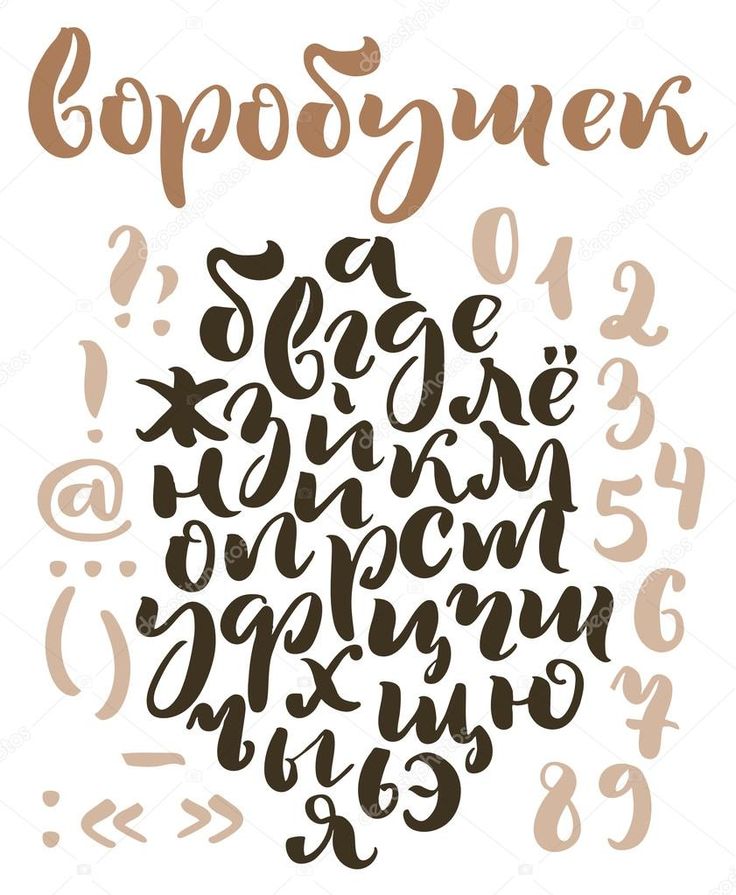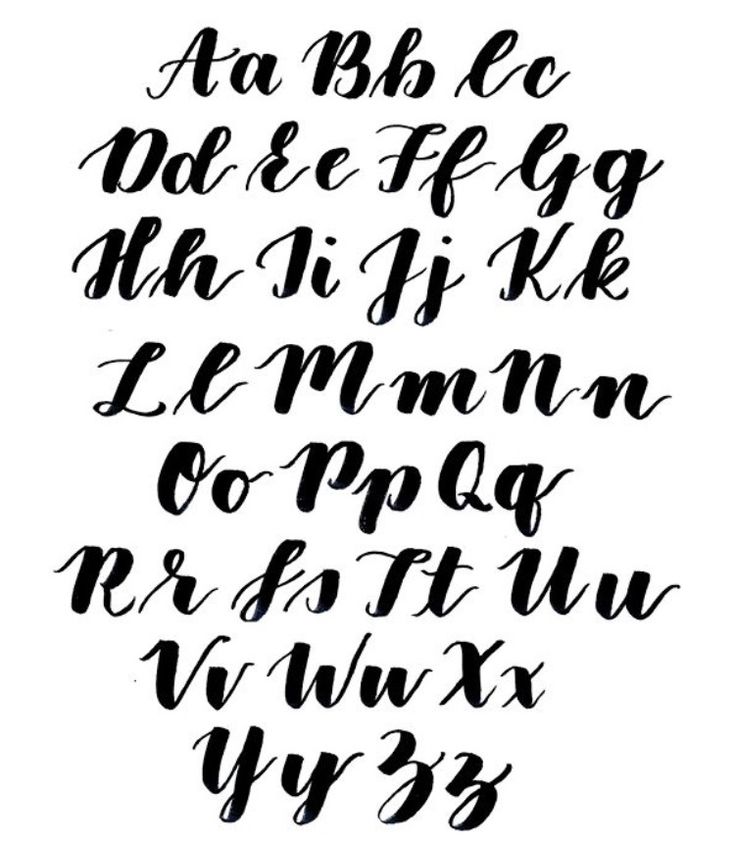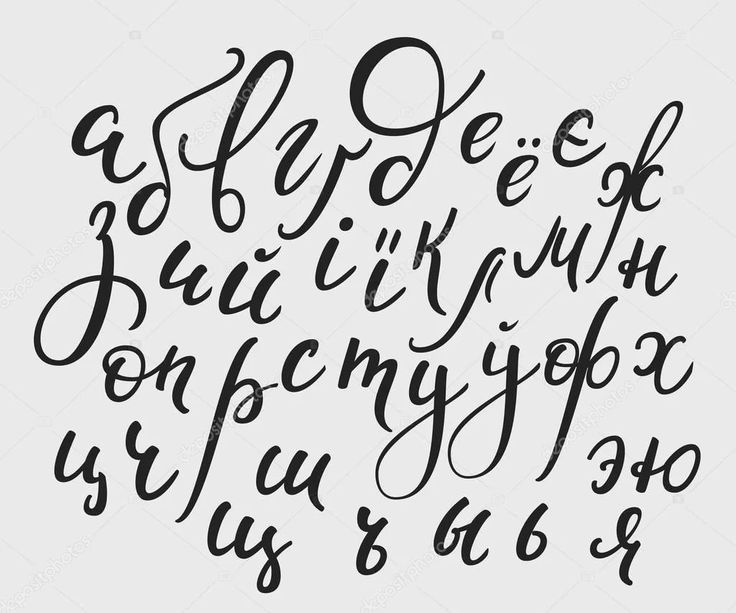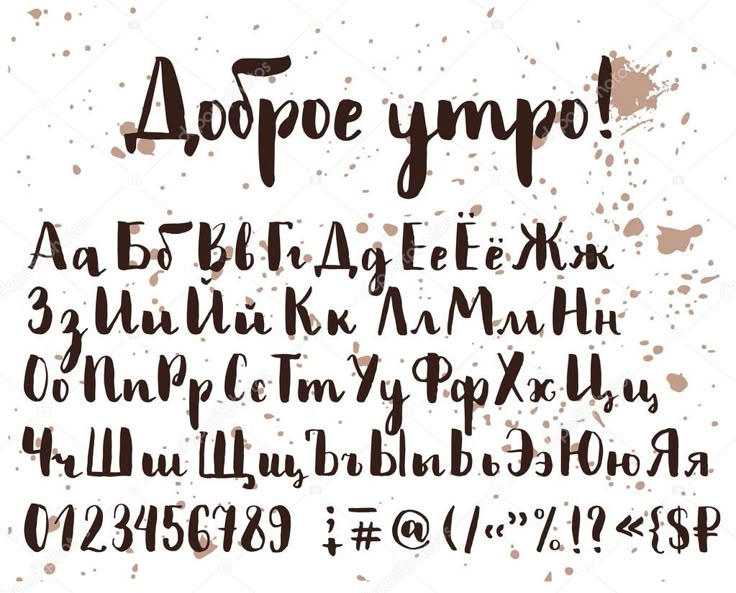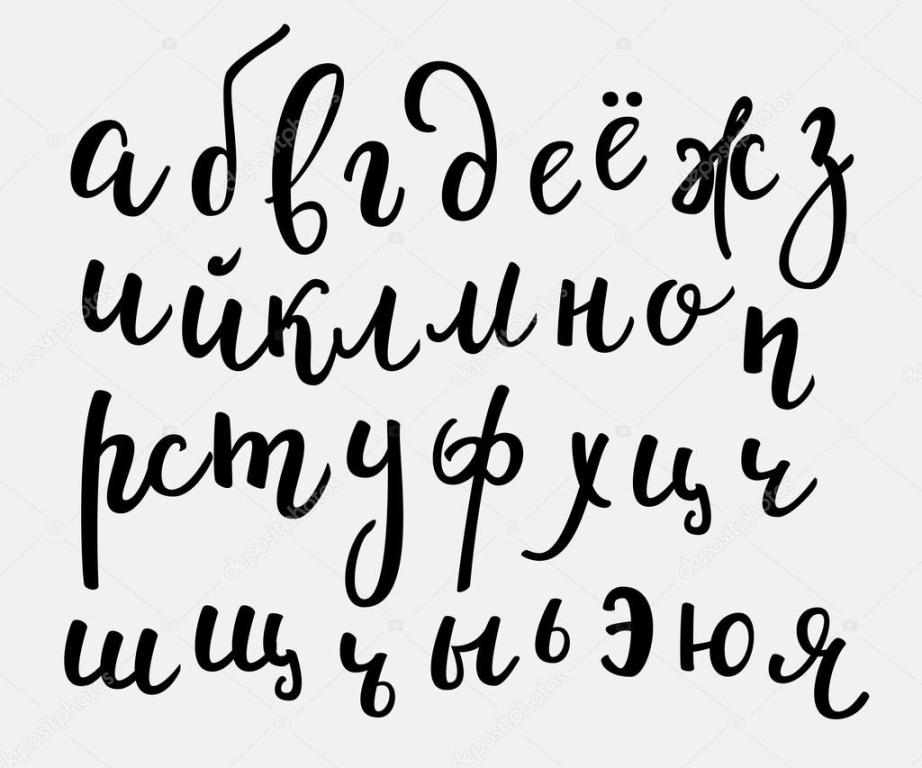
что это такое, чем отличается от каллиграфии
Современный человек окружен рекламой буквально со всех сторон: это и афиши, и баннеры, реклама по телевизору и радио и еще множество других нативных способов, которыми пользуются опытные маркетологи. Одна из последних модных тенденций, которая очень полюбилась дизайнерам, называется леттеринг. Что это такое и почему оно с каждым днем набирает все большую популярность? Давайте разбираться.
Интересное из истории
Каждый знаком с понятием каллиграфии, ведь оно возникло очень давно и сопровождает человека на протяжении всей истории. Сейчас каллиграфия считается атрибутом или даже целым отдельным видом искусства. Однако в далеком прошлом искусство красиво писать имело под собой и практическую почву. Монахи переписывали огромные рукописи и создавали настоящие шедевры, используя самые сложные техники каллиграфии.
Возникла каллиграфия в Древней Греции, в переводе это слово обозначает «красивый почерк». Греко-римское письмо имело свои особенности и отличительные черты от восточно-азиатского алфавита.
При написании текстов даже использовались разные инструменты, так, к примеру, греки писали пером, а китайцы пользовались тушью и кисточками.
В отличие от каллиграфии леттеринг (что это такое, мы разберем чуть ниже) возник в прошлом столетии как яркий и эффективный инструмент рекламы любого товара. Однако сейчас он успел стать течением современного исскуства, к которому обращаются все большее количество дизайнеров, шрифтовых и арт-художников.
Отличия леттеринга от каллиграфии
Многие ошибочно предполагают, что эти два понятия являются одинаковыми по значению. Однако леттеринг, прописи которого рисуются дизайнерами, и каллиграфия — это два абсолютно разных способа написания букв. Если в каллиграфии существуют определенные правила и ограничения, то во втором случае нет никаких границ, художник вправе создавать любые шедевры и воплощать свои самые смелые идеи.
Само слово «леттеринг» с английского языка означает «писать письмо». Основная черта этого направления заключается в том, что это целый рисунок, который состоит из букв и других графических знаков.
Особенности леттеринга
Алфавит, написанный в этом стиле, не имеет своих аналогов, поэтому ни в коем случае нельзя считать леттеринг шрифтом. Ведь шрифт — это готовый набор букв, написанных определенным образом, которые повторно используются много раз. В леттеринге же каждая буква имеет свой неповторимый наклон, толщину и динамику.
Пожалуй, еще одним различием каллиграфии и леттеринга (шрифты считаем отдельным инструментом) является то, что в каллиграфии присутствуют только прописные буквы, запрещены какие-либо добавочные линии и любые мелкие рисунки. А в последнем каждая буква оформляется уникальным образом, дополняется самыми разными картинками и знаками.
Кто этим занимается?
Итак, мы разобрали основы леттеринга: что это такое и в чем его различия от привычной нам каллиграфии. Однако остается еще много вопросов, например, люди какой профессии занимаются леттерингом?
Теоретически, этим может заниматься абсолютно любой желающий, и неважно для каких целей.
Существует множество специальностей, связанных с леттерингом. Вот самые известные:
- типограф, который разрабатывает не только шрифты, но и стили оформления в целом;
- маркетолог-дизайнер, создающий настоящие шедевры рекламы;
- художник, который творит ради искусства;
- тату-мастера, являющиеся самыми молодыми специалистами в этой нише.
Всех этих людей объединяет любовь к волшебному леттерингу, алфавиту (русский или же иностранный — это совсем не важно, ведь текст, написанный с любовью, будет красив на любом языке).
Инструменты для творчества
Древние каллиграфисты писали пером и чернилами. Интересно, а современные художники смогли бы творить шедевры, используя лишь этот примитив? Давайте посмотрим, какими же приспособлениями порадовал специалистов XXI век высоких технологий.
Существует огромное количество самых разных «приблуд» для творческих натур, решивших заняться леттерингом. Для начинающих и для профессионалов имеются свои инструменты.
Итак, вот самые популярные канцелярские принадлежности, которые точно нам пригодятся:
- Брашпены — это инструменты, снабженные картриджем. Напоминают обычную кисть, только их не нужно никуда макать. Они имеют множество различных насадок, форм, даже материал наконечника может быть разным. Цветовая гамма представлена в широком ассортименте. По типу брашпены делятся на три вида: на водной основе, на спиртовой и на гелевой.
- Рейфседеры, колапены — это все инструменты, напоминающие обычную железяку с острым концом. Они обычно идут в наборе с чертежной готовальней. Ими очень удобно рисовать графический леттеринг. Шрифты получаются в готическом стиле.
- Маркеры и электронные перья от производителя Molotow — это самая современная продукция для дизайна и рисования граффити.
- Параллель пен — это металлическая ручка с заменяющимся картриджем. Ее отличительная особенность в том, что она имеет оригинальную конструкцию: вместо плоского пера в ней есть две пластины. Благодаря им получается более насыщенный отток чернил.
Русский Алфавит содержит 33 буквы — 10 гласных и 21 согласную, а также два знака — твердый и мягкий — которые не имеют собственных звуков и влияют только на соседние буквы.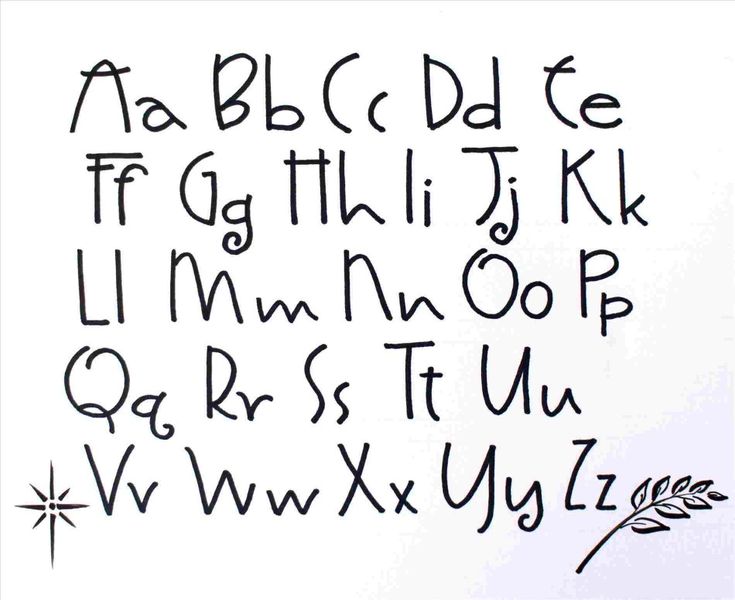